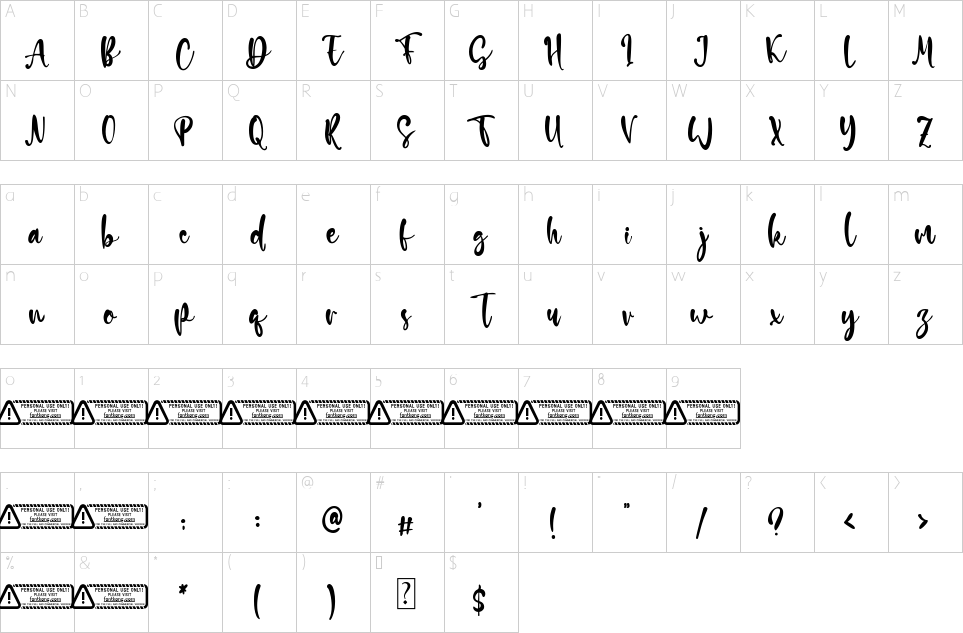
Daniel Rachel Font – Download Grátis
A fonte “Daniel Rachel” é uma opção interessante para designers que buscam estilos naturais e envolventes. Desenhada pela Font Kong, esta font está disponível tanto para sistemas Windows quanto Mac. Com sua simplicidade e elegância, a Daniel Rachel pode ser usada em diversos ambientes gráficos digitais, como títulos de slides ou textos decorativos. Seu design minimalista cria um contraste suave com outros elementos visuais, tornando-a perfeita para aplicativos de marketing digital ou editoriais online. Com um design cuidadosamente elaborado e uma popularidade de 1.017 downloads, “Daniel Rachel” é uma escolha confiável entre os muitos recursos gratuitos disponíveis para designers que valorizam elegância e simplicidade em suas criações digitais.